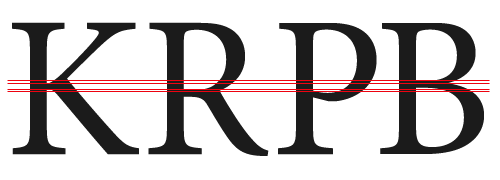
Name des Strichs beim R
kann mir jemand sagen wie man den Strich nennt der beim R nennt der von der Punze weggeht?
und Punze, ohne t. :-) (von lat. pungere: stechen)
Schwanz, Schweif, Abstrich, Bein, Auslauf, Fuß, ...
Wenn es eindeutig ist (im Bezug auf das "R"), stimmt es. Da keiner der Begriffe für einen anderen Teil des "R" stehen kann, passen sie alle.
Wobei mir Spielbein jetzt am besten gefällt, aber verwendet hab ich es bisher noch nicht.
Ja, genauer gesagt, das „Spielbein“. Das R ist ja nur ein P, dass im Kontrapost steht. :hammer:
Nein, eben nicht. Anders als Michelangelos »David« hat das »P« ja weder Stand- noch Spielbein, sondern nur einen Stamm (Schaft, Grundstrich). Also nix mit Hüftschwung, Gewichtsverlagerung o. ä. Und dass das »R« eben nicht ein »P« mit angenageltem Bein ist, beweist ja diese Grafik:
:) Ich hoffe dass sich meine Schriften auch so schön vermaßen lassen ... ich zeichne da einfach drauf los und schaue dass es harmonisch aussieht (und außerdem, dass niemand anderes das dann abschaut und zeug reininterpretiert woran ich selbst nie gedacht habe).
Drum find ich das "Anatomie der Buchstaben" auch schön als Bilderbuch, aber irgendwie wenig nützlich.
Edit: Puh... sie lassen sich so schön vermaßen.
Das ist mir doch alles bekannt. Ich hätte vieleicht nur schreiben sollen, dass das R im Kontrapost steht!
... das war doch auch nicht wirklich ernst gemeint.